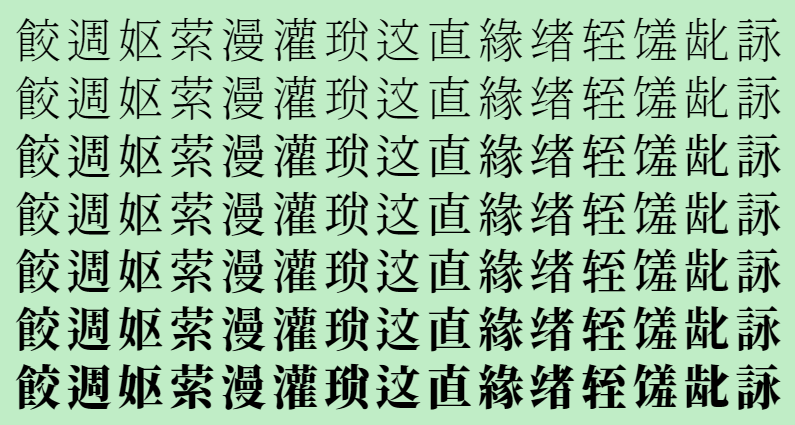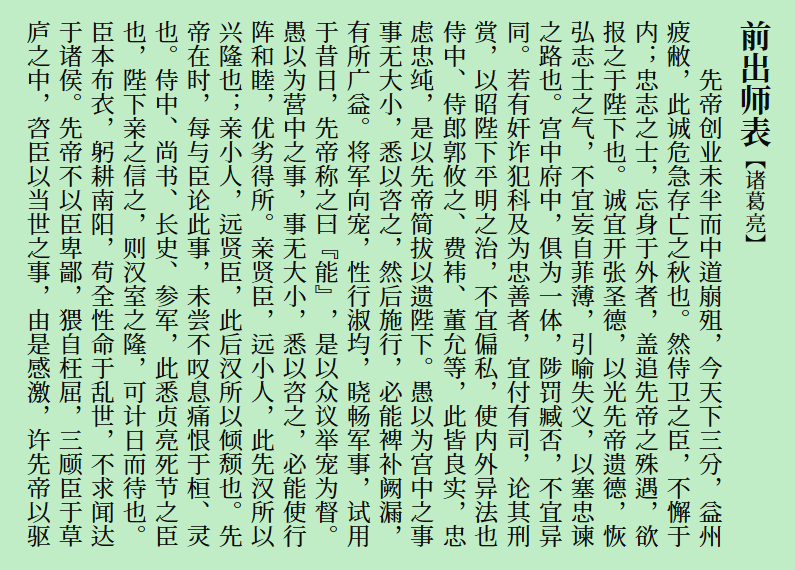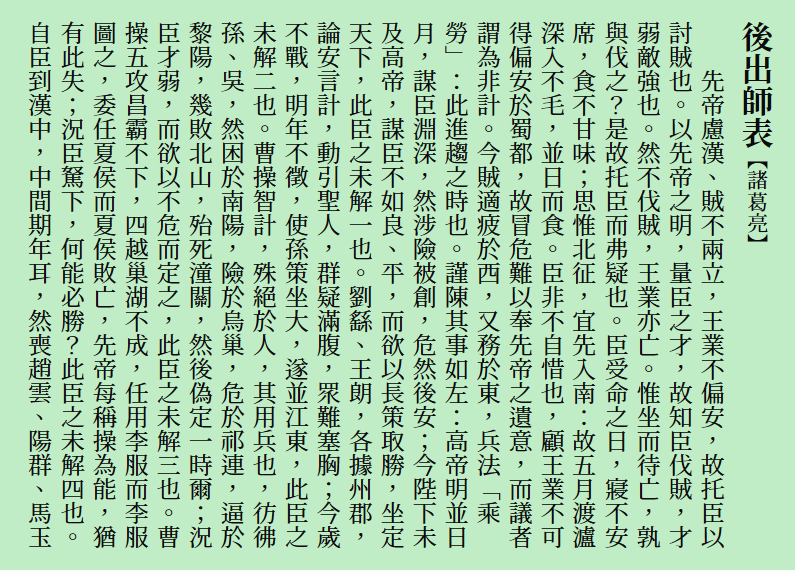
Early Summer Serif 初夏明朝体
初夏明朝体是一款贴近传统印刷风格的中文字体,字形端正利落,用于长篇版面阅读起来很顺畅。它以思源宋体为底层架构,在此基础上重新调整了部分笔画的比例与重心,既保留了原本的扎实感,也让视觉呈现更加柔和舒展。
诸葛亮《前出师表》竖排文本,内容讲述先帝崩殂、危急存亡及亲贤臣远小人的谏言。-刊刻Kntuk
诸葛亮《后出师表》竖排繁体文本,阐述汉贼不两立及北伐讨贼的决心与局势分析-刊刻Kntuk
NOTE: 本字体可通过 locl 特性改变不同的标点符号。
包含可变字体,以及 7 种粗细的静态字体,使用 TrueType 和 OpenType 格式。本项目还提供了适合屏幕显示的“屏阅初夏明朝体”。
浅绿色背景上排列着七行相同的黑色中文字符,内容为鲛週妪萦漫灌琐这直緣绪轻馐龀詠-刊刻Kntuk